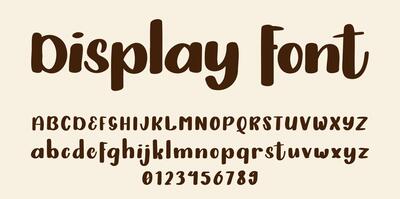
Apa Itu Font Display
Apa Itu Font Display – Kita pasti sering dengar tentang font display, font display sering digunakan untuk menampilkan judul, tajuk, atau pesan yang ingin disampaikan dengan kuat dan menarik. Jadi, apa sih sebenernya rahasia dibalik huruf-huruf keren ini? Yuk, kita gali lebih dalam!”
Apa Font Display Itu?
Font display adalah jenis font yang dirancang khusus untuk penggunaan pada judul, tajuk, atau teks yang ditonjolkan dalam desain grafis. Font display sering kali memiliki karakteristik yang menarik perhatian, unik, dan ekspresif, sehingga cocok untuk digunakan dalam situasi di mana teks tersebut perlu mencuri perhatian dan menarik minat pembaca atau pemirsa.
Berbeda dengan font serif atau sans-serif yang dirancang untuk keterbacaan dan penggunaan dalam teks panjang, font display lebih ditujukan untuk menampilkan pesan secara singkat dan menonjol. Karakteristik font display bisa bermacam-macam, mulai dari yang bergaya retro, artistik, hingga yang futuristik atau eksperimental.
Berikut Adalah Beberapa Penggunaan Font Display:
1. Judul Website: Font display sering digunakan untuk judul halaman web atau banner yang ingin menarik perhatian pengunjung.
2. Desain Poster: Dalam desain poster, font display digunakan untuk judul utama atau slogan yang ingin disampaikan dengan kuat dan jelas.
3. Logo dan Branding: Beberapa merek menggunakan font display dalam desain logo mereka untuk menciptakan identitas yang unik dan mudah dikenali.
4. Kemasan Produk: Font display seringkali dipilih untuk kemasan produk untuk menyoroti merek atau nama produk dengan tampilan yang menarik.
5. Desain Merchandise: Kamu dapat menggunakan font ini untuk design merchandise untuk memberikan pesan yang kuat dan menonjol.
Kelebihan font display adalah kemampuannya untuk menarik perhatian secara instan dan menyampaikan pesan dengan gaya yang kuat. Karena karakteristiknya yang unik, font display biasanya tidak cocok untuk penggunaan dalam teks panjang atau penggunaan dalam skala kecil, karena dapat mengganggu keterbacaan. Oleh karena itu, penggunaan font display sebaiknya disesuaikan dengan konteks dan tujuan desain yang diinginkan.